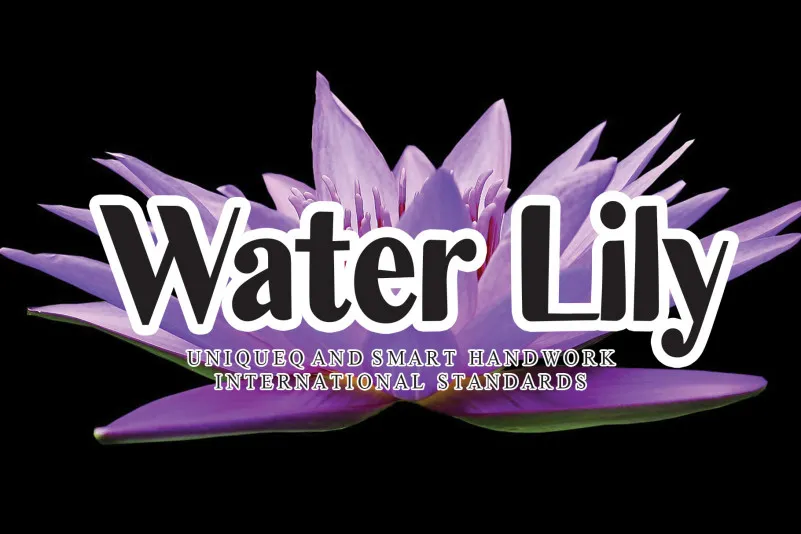
A fonte “Water Lily Display Font” é uma serifada simples e elegante, perfeitamente adequada para diversos projetos de design. Seu estilo natural e casual faz dela uma escolha ideal tanto para designs formais quanto para momentos mais descontraídos. Sua tranquilidade gráfica permite que você adorne seu trabalho com um toque sofisticado sem sacrificar o conforto visual ou a legibilidade. Ideal tanto para logotipos quanto para textos, essa fonte é uma ótima escolha para quem busca um equilíbrio entre modernidade e elegância em seus projetos de design. Com sua simplicidade e beleza natural, “Water Lily Display Font” será certamente uma das suas novas favoritas.